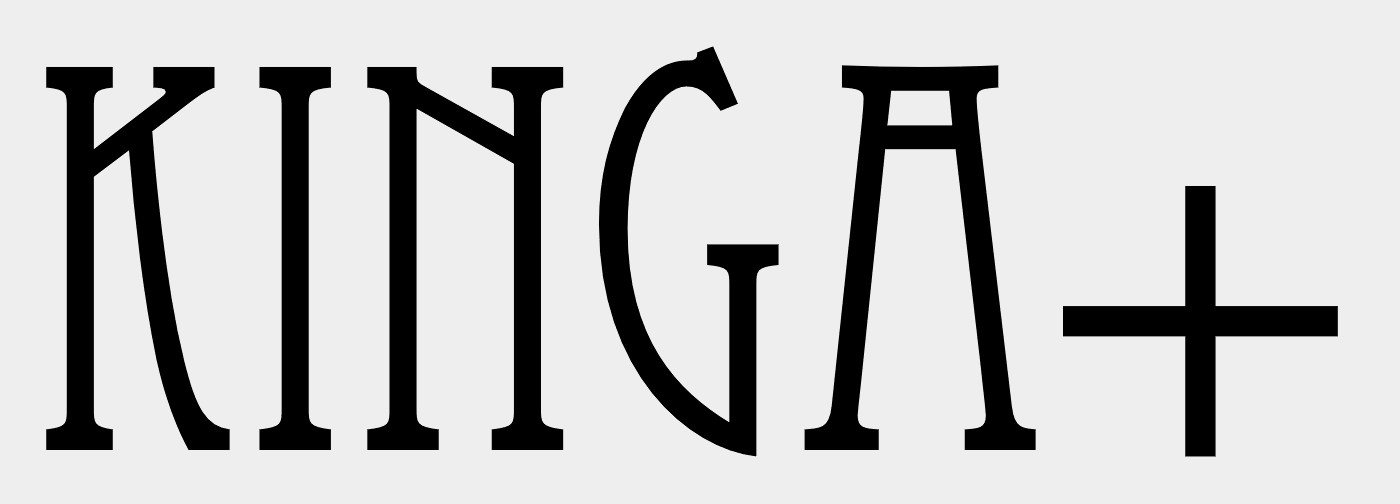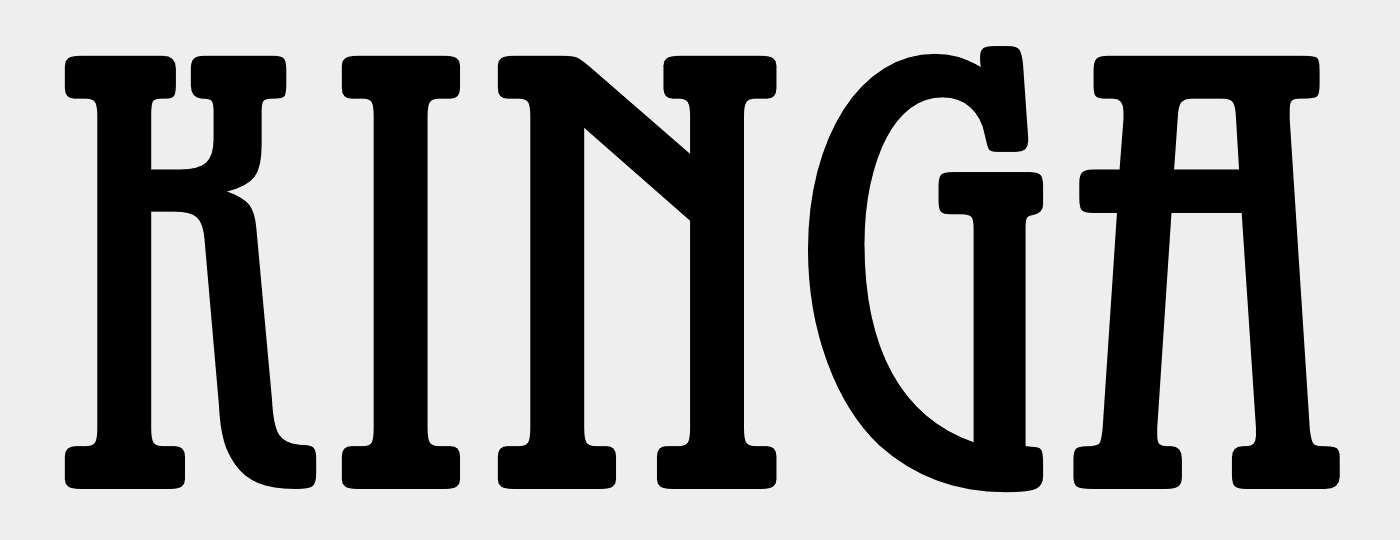
Vielleicht kennt jemand diese Schrift...
Eine Suche nach "Art Deco" könnte dich weiterbringen. Das gezeigte Beispiel ist vermutlich auf 50% seiner ursprünglichen Breite gestaucht.
Ähnlich wäre die
Wahrscheinlich ist es die Eccentric. Allerdings wirklich arg zusammengequetscht, dabei wäre doch genug Platz um sie ohne diese Mißhandlung zu verwenden.
Die Schrift gibt es von verschiedenen Anbietern. Die obere von Solotype, ist billiger und hat auch Kleinbuchstaben. Die untere von Adobe ist wesentlich besser gezeichnet.